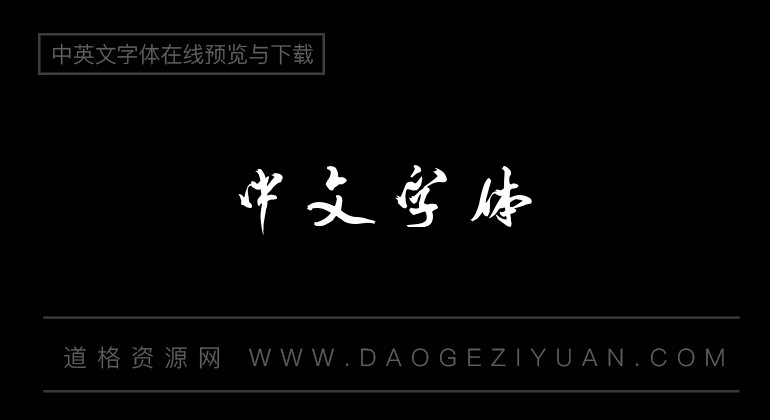
书体坊向佳红毛笔行书
书体坊向佳红毛笔行书字体,是一款经典的毛笔行书字体,由书体坊设计师潘佳红创作而成。它以毛笔行书的传统笔画为基础,结合现代设计理念,将传统毛笔行书字体和现代设计元素融合在一起,让字体看起来既有趣又现代。它具有流畅的笔画,温柔的线条,清晰的轮廓,确保存在良好的可读性和可视性。在排版上,它具有优异的可塑性,可以很好地满足排版师的需求,使排版作品更具艺术性。
书体坊向佳红毛笔行书是一款非常不错的手写艺术字体,具有很好的视觉感,适合于文化类的宣传设计、商业类品牌的广告和产品包装设计以及个性化文字排版等较多场景。